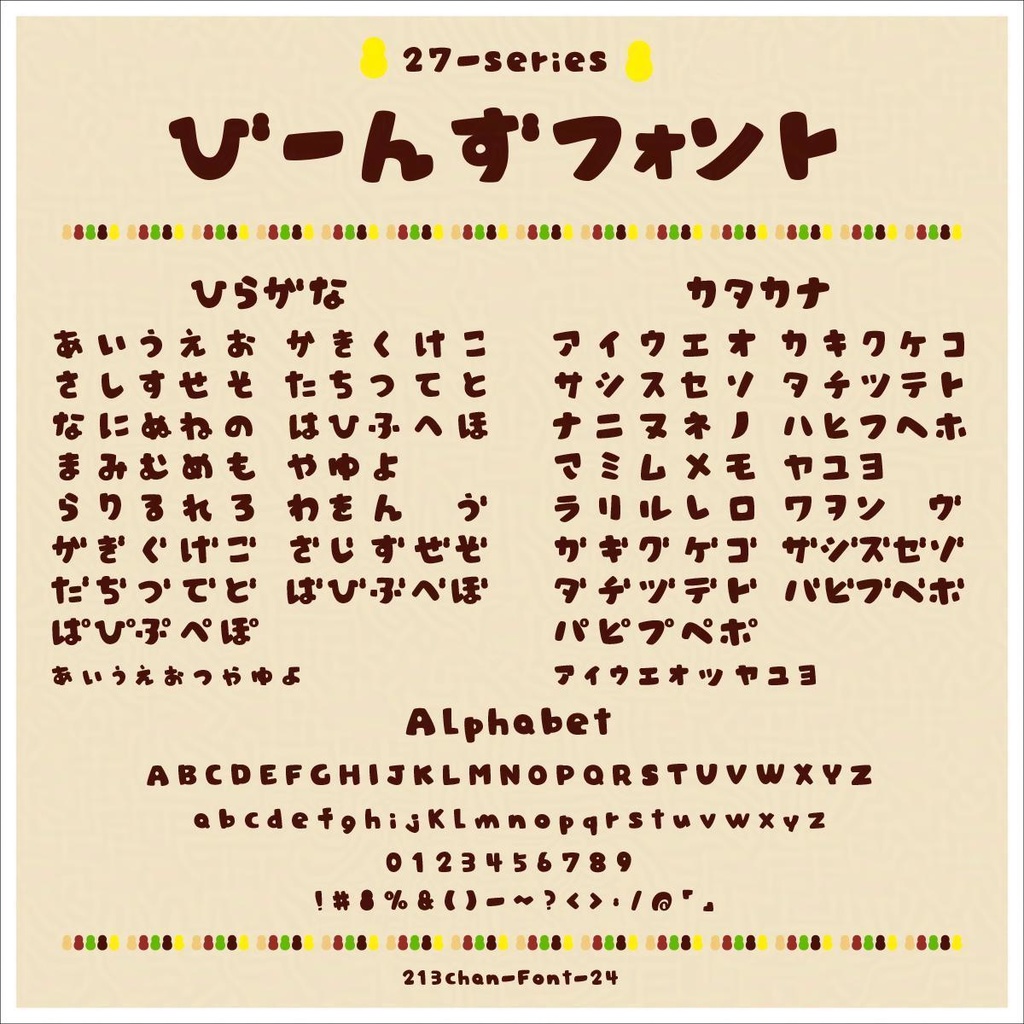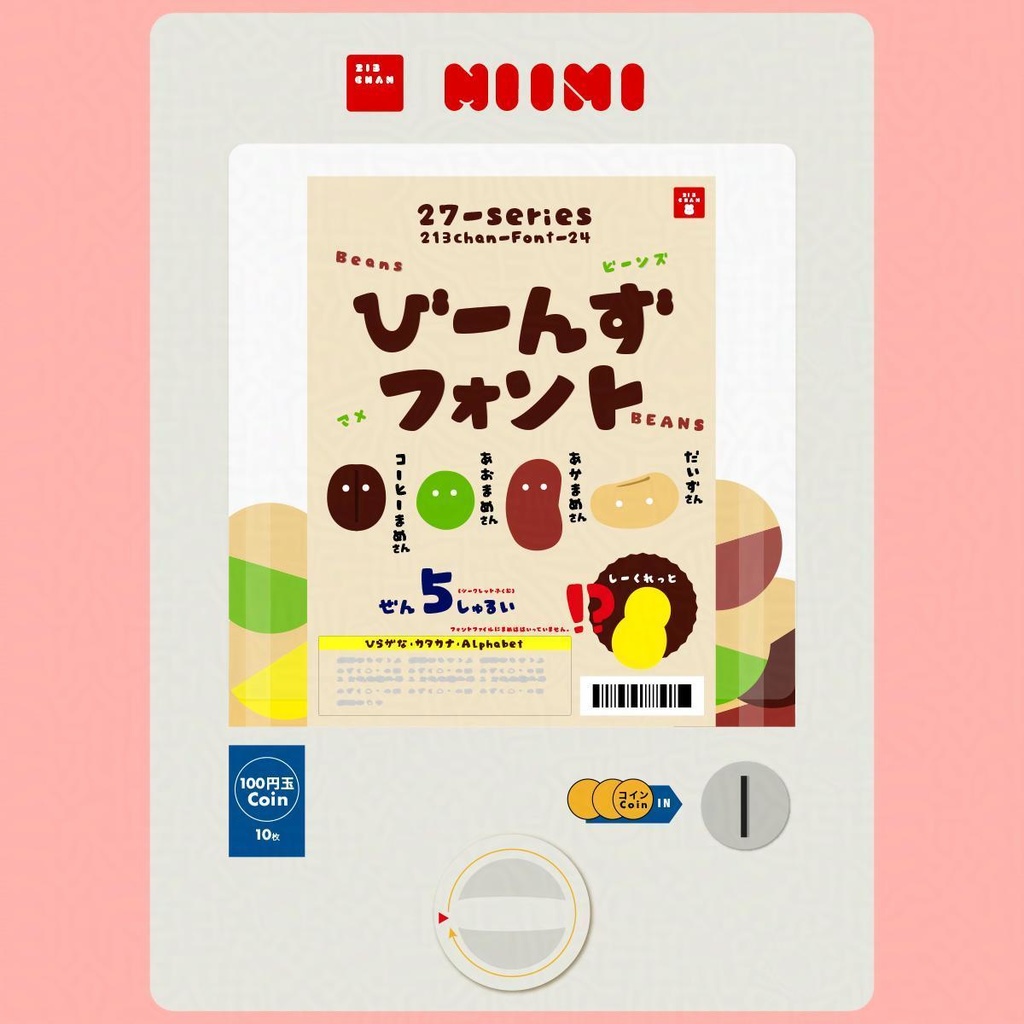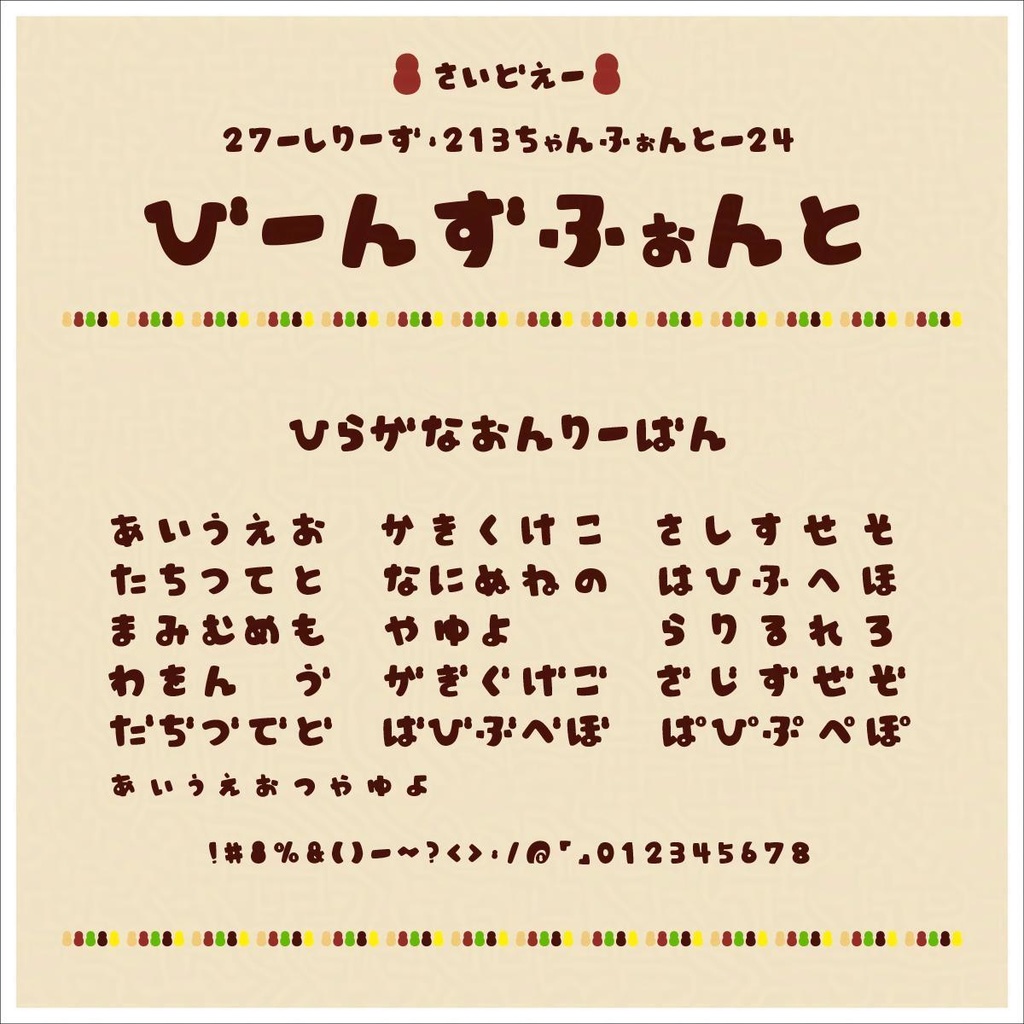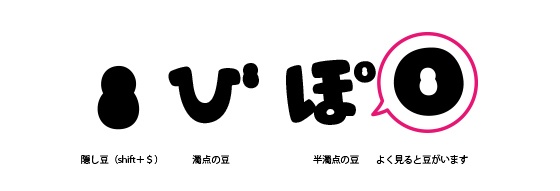
びーんずフォント(27-nina-Beans_font)【商用可】ひらがなのみフリー版あり
27-nina-Beans_font(びーんずフォント)は213ちゃんが作った24個目の商用可能な、濁点・半濁点に、びーんず(豆)をあしらったコミック風手書きの可愛いフォントです! 注意※これはガチャガチャ風の書体見本でフォントで豆類5種は入っていません ひらがなのみの、フリーフォント版のお試しでよかったら 有料版をおすすめします! 無料フリーフォント版:【商用可】 27-nina-BeansA ひらがな・数字記号のみ版フリー 声援:有料DLで応援!【商用可】 27-nina-Beans 欧文(大小)・ひらがな・カタカナ・数字・記号 印刷物・ゲームやWeb、YouTubeのサムネイルやタイトルデザインなどにいかがでしょうか? 基本フリーですが、当フォントを利用した制作物などを、SNSで教えてくれると励みになります。 制作note https://note.com/sweet_2727/n/n6ae44a875862 【収録内容】欧文(大小)・ひらがな・カタカナ・数字・記号 【Readme】フォントご使用上の注意 ・フォントの著作権は、213ちゃんに帰属します。 ・可愛がってくださるとうれしいです。 ・無断転載・再配布は堅くお断りいたします。 ・DLしたフォントに起因する損害は補償致しかねますので予めご了承ください。 ・使用する際の不明点はお問い合わせ先にご連絡ください。答えられる範囲でお返事いたします。 英文 This font (213chan font) is a free OpenType font that can be used for commercial and personal web and print designs. Please take care of me. Font copyright belongs to 213chan. Unauthorized reproduction, redistribution, resale, and trademark registration of logos created using fonts is strictly prohibited. Please note that we cannot compensate for damage caused by DL fonts. Please note that we do not provide support regarding installation or usage.